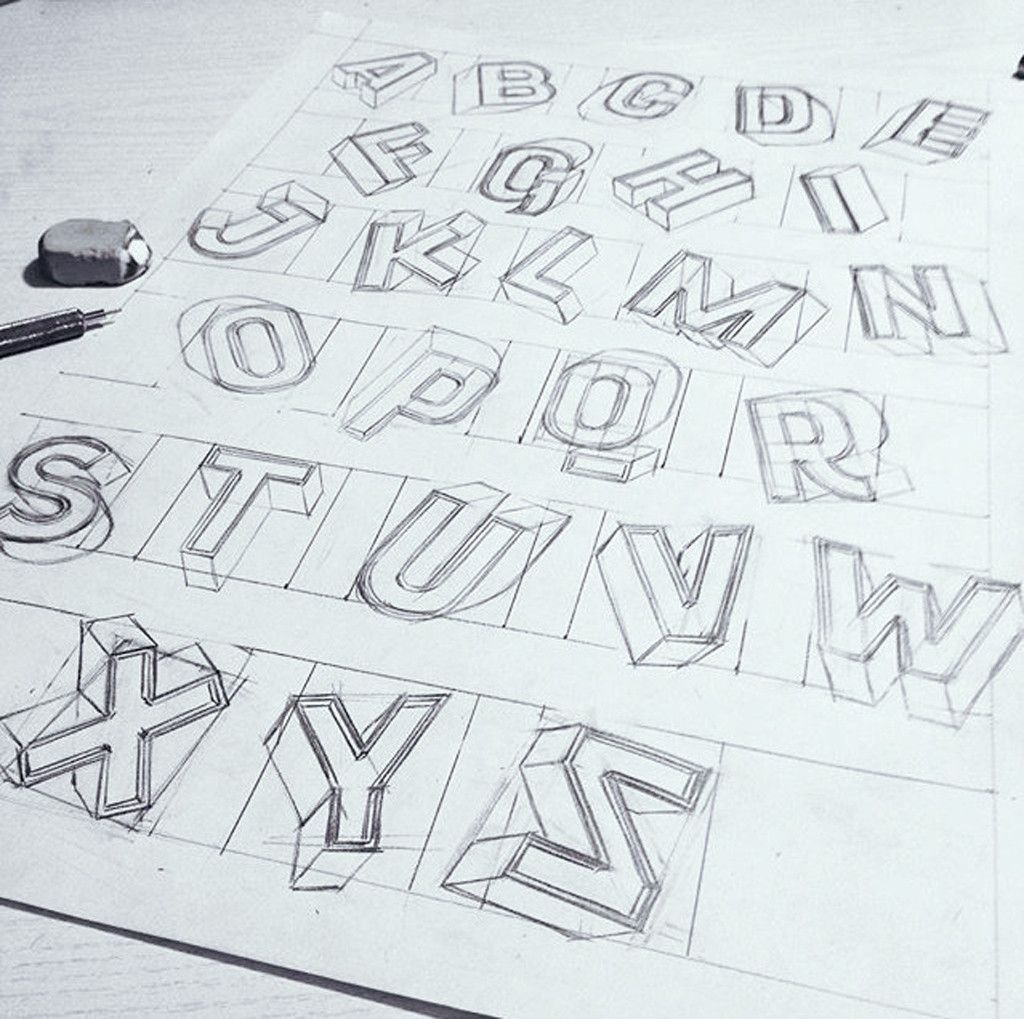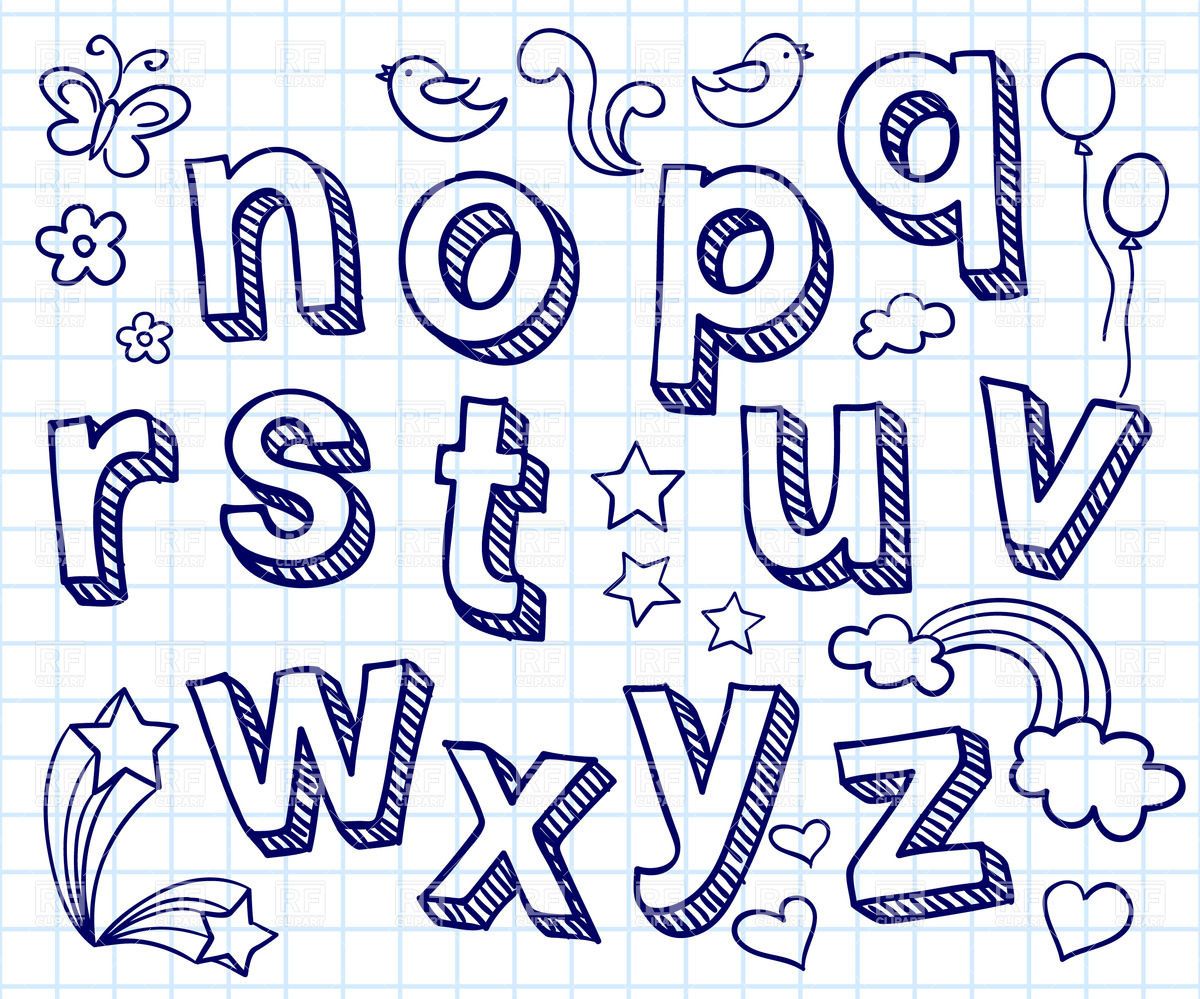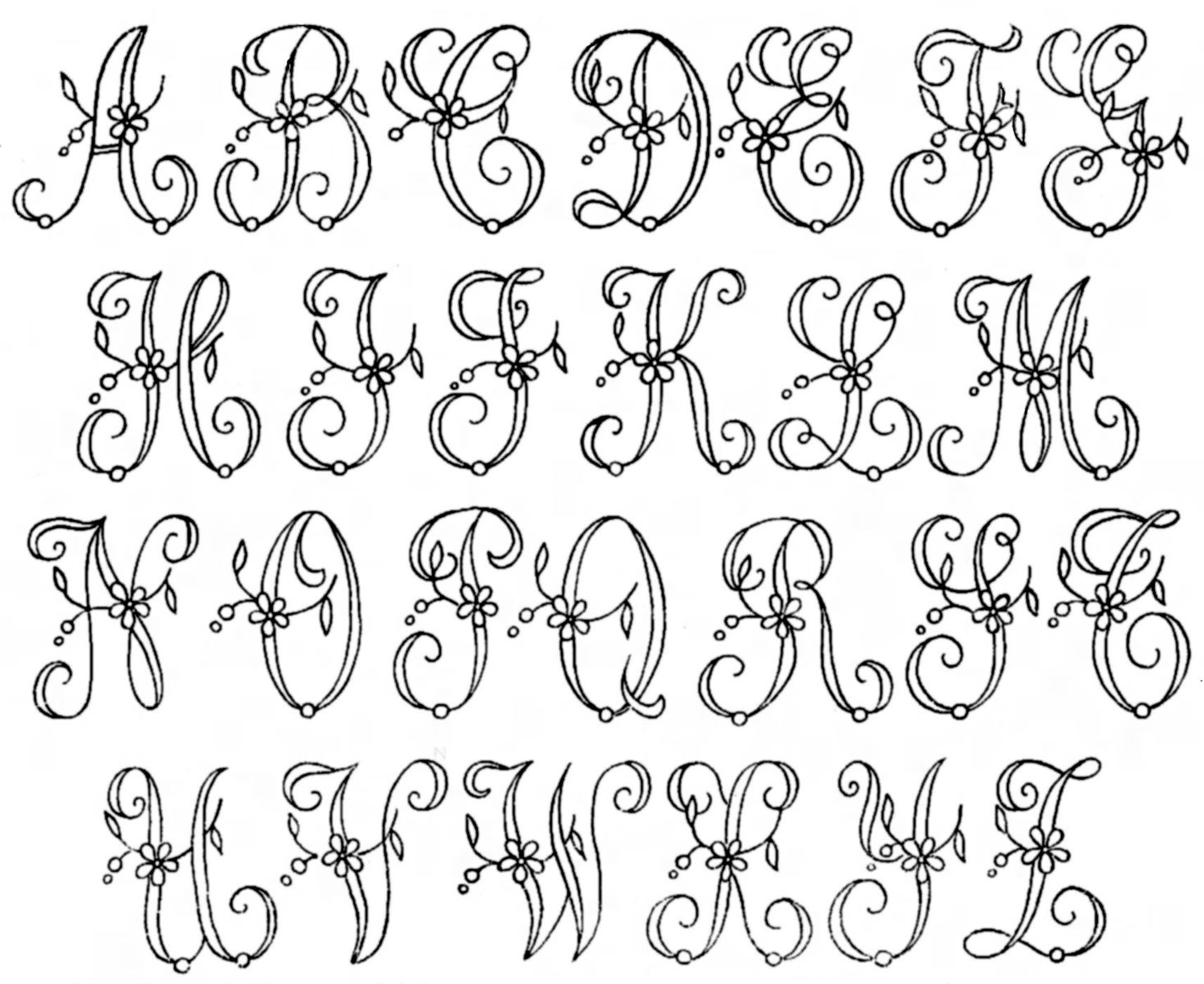
Шрифты для рисования: Основы рисования и создания собственного рукописного шрифта
Основы рисования и создания собственного рукописного шрифта
Вы когда-нибудь хотели придать своим цифровым макетам и дизайну по-настоящему индивидуальный подход? В этом уроке мы рассмотрим, как вы можете создать шрифт из вашего собственного почерка для использования на вашем компьютере.
Учебник будет разделен на три части. Во-первых, мы рассмотрим основы рисования шрифта. Затем, как только мы разогреемся, мы увидим, как вы можете оптимизировать свой почерк для обеспечения высокого качества и универсальности. И, наконец, мы проанализируем несколько различных способов переноса шрифта на компьютер и преобразования нарисованных от руки букв в цифровой шрифт.
1. Практика рисования Тип
Вероятно, вы пишете набросанные заметки или списки каждый день, но редко замечаете свой почерк.
Вы должны сначала войти в более естественный способ письма. Я считаю, что лучший способ сделать это — попрактиковаться в рисовании шрифта. Это также очень полезно, так как позволяет вам лучше понять ключевые характеристики гарнитуры и дает вам возможность распознавать общие черты (согласованности) между различными символами внутри гарнитуры. Это окажется полезным, когда мы начнем улучшать свои собственные рукописные символы и оптимизировать их для оцифровки.
Шаг 1
Положите линейку поперек страницы под горизонтальным углом настолько прямо, насколько это возможно. Возьмите заостренный карандаш и, слегка надавливая, нарисуйте линию над верхним краем линейки.
Если ваша линейка представляет собой стандартизированную линейку шириной 30 мм, вы можете оставить линейку на месте и провести вторую линию вдоль нижнего края линейки. Это дает преимущество в том, что обе линии идеально параллельны.
Выделите верхнюю треть 10 мм от общей высоты между линиями и нарисуйте третью горизонтальную линию линейкой и карандашом, нажимая более слегка, чтобы сделать слегка более тусклую линию. Эта линия представляет высоту х. Подчеркните ваши типографские термины, такие как x-height и baseline, в моей статье о типографии от A до Z.
Шаг 2
Вы можете повторить последовательность строк, используя те же измерения из шага 1, чтобы создать страницу, заполненную линиями. Это ваша собственная сетка для письма, на которой вы можете попрактиковаться в рисовании шрифтов.
Шаг 3
Выберите классический шрифт с засечками, такой как Adobe Caslon Pro, который показан здесь, или Garamond. Чтобы попрактиковаться в рисовании шрифта, лучше сначала выбрать шрифт с засечками, так как шрифт без засечек имеет более тонкие особенности и может быть сложнее рисовать точно, если вы новичок.
Введите следующие символы: «H n o y» с пробелом между ними. Это хорошие символы для выбора, так как они отображают ряд различных функций: два вертикальных стержня и поперечина на «H», апертура и засечки на «n», полностью закрытый счетчик на «o» и стремительный спуск и диагональные рычаги в нижнем регистре ‘у’.
Если вы работаете в InDesign, вы также можете включить базовую сетку («Просмотр»> «Сетки и направляющие»> «Показать базовую сетку»), чтобы легче было видеть, как пропорции символов совпадают друг с другом.
Взорвать символы в большом масштабе на экране или увеличить. Теперь вы можете начать рисовать символы. Чередуйте использование линейки и рисование штрихов от руки. Не беспокойтесь, если ваши попытки выглядят немного сумбурно — цель этого упражнения состоит в том, чтобы вы освоились с типом рисунка и наблюдали характеристики шрифта и сходства (или различия) между каждым символом.
Вы заметите, что шрифты с засечками основаны на принципах симметрии и порядка. Вытяните штрихи от края символов и обратите внимание на углы и пропорции. Стебли почти всегда имеют одинаковую ширину, независимо от символа, но вы можете заметить, что размер засечек немного больше в верхнем регистре «H». Также обратите внимание, что некоторые части персонажей тоньше; эти виды инсульта называются волосками.
Шаг 4
Хотя мы не будем применять все эти характеристики к нашему рукописному шрифту, очень важно признать, что все шрифты регулируются набором правил, будь то формальный, который чаще встречается с типом засечек и без засечек, или неформальный, который чаще встречается у нарисованных от руки, нарисованных или рукописных шрифтов.
После того, как вы потренировались рисовать шрифт или несколько шрифтов, если хотите, вы должны начать немного изучать рукописные шрифты, чтобы помочь вам подумать о том, как вы хотите, чтобы ваш рукописный шрифт был организован.
Перейдите на сайт ресурсов шрифтов, например FontSquirrel или DaFont, и посмотрите на доступные там рукописные шрифты. Выберите шрифт, который, по вашему мнению, разделяет качества с вашим собственным почерком, и загрузите его.
После того, как вы попрактиковались в рисовании шрифта или, если хотите, нескольких шрифтов, вы должны начать небольшое исследование рукописных шрифтов, чтобы понять, как вы хотите, чтобы ваш рукописный шрифт был организован.